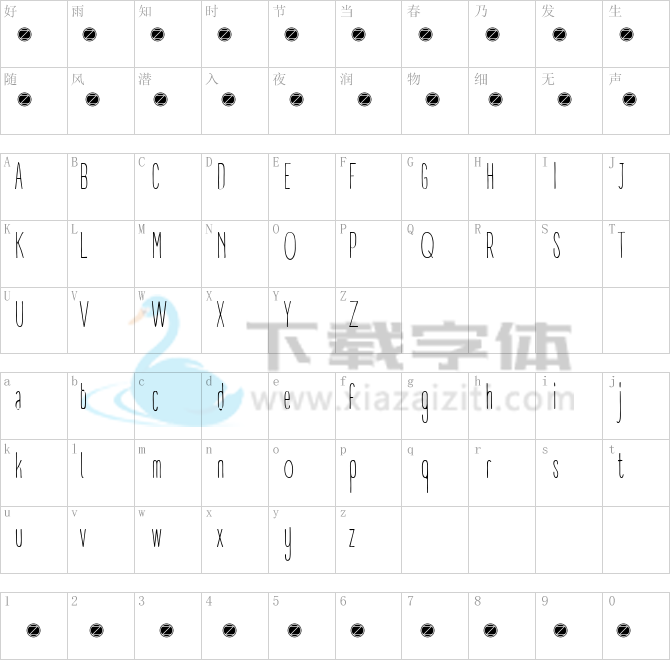
A DAY WITHOUT SUN.otf字体下载,这款字体结构工整、笔画清晰,兼顾美观与易读性,适用于标题、正文、海报、包装、LOGO 等多种场景。字形优雅稳定,风格百搭耐看,适配日常排版与创意设计,让文字呈现更舒适、更具质感。A DAY WITHOUT SUN.otf字体下载一笔一画,皆是细节,以均衡的比例、流畅的线条打造舒适视觉体验,字形端正大气,风格简约现代。无论是商业设计、品牌宣传还是日常排版,都能轻松驾驭,让文字更有格调与力量。A DAY WITHOUT SUN.otf字体下载字体下载。